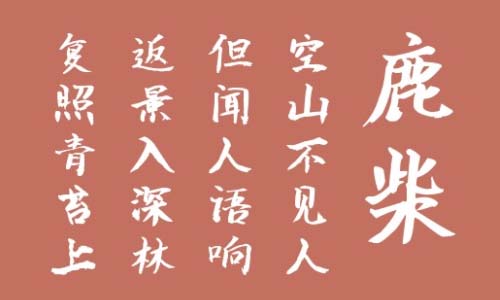
南構麗萍手寫體字體是一款由葉麗萍手寫創(chuàng)作的字型,比起眾多的硬筆手寫字體,南構麗萍手寫體更偏向于毛筆手寫風格,其整體效果出色,能夠應用于文本裝潢、信息展示、網(wǎng)頁設計、篆刻制模、數(shù)據(jù)制作、裝潢設計、計算藝術設計、視覺設計、字帖等一切合法應用場景,歡迎大家前來下載。